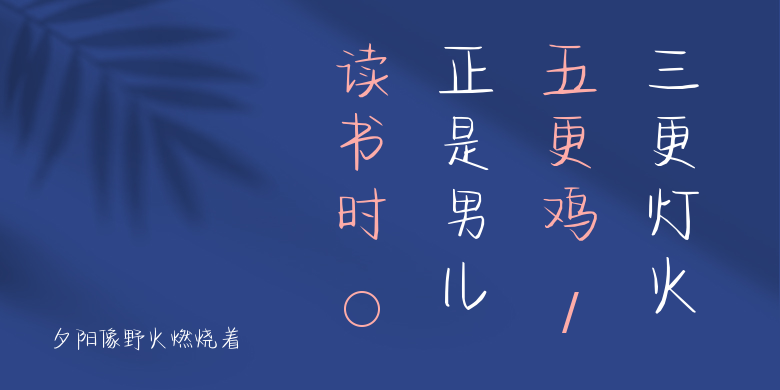
夕阳像野火燃烧着
夕阳像野火燃烧着,这款字体结构工整、笔画清晰,兼顾美观与易读性,适用于标题、正文、海报、包装、LOGO 等多种场景。字形优雅稳定,风格百搭耐看,适配日常排版与创意设计,让文字呈现更舒适、更具质感。夕阳像野火燃烧着一笔一画,皆是细节,以均衡的比例、流畅的线条打造舒适视觉体验,字形端正大气,风格简约现代。无论是商业设计、品牌宣传还是日常排版,都能轻松驾驭,让文字更有格调与力量。夕阳像野火燃烧着字体下载。